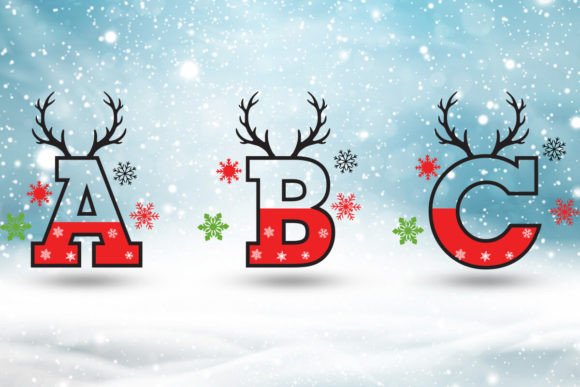
Christmas Alphabet Letters Sublimation
適切なデザイン要素を見つけるのは難しい場合がありますが、Christmas Alphabet Letters Sublimationは作品を即座に引き立てる優れたコレクションを提供します。
精密に作られたChristmas Alphabet Letters Sublimationは、クリーンなベクター、滑らかなタイポグラフィ、そして安心のための商用ライセンスを提供します。